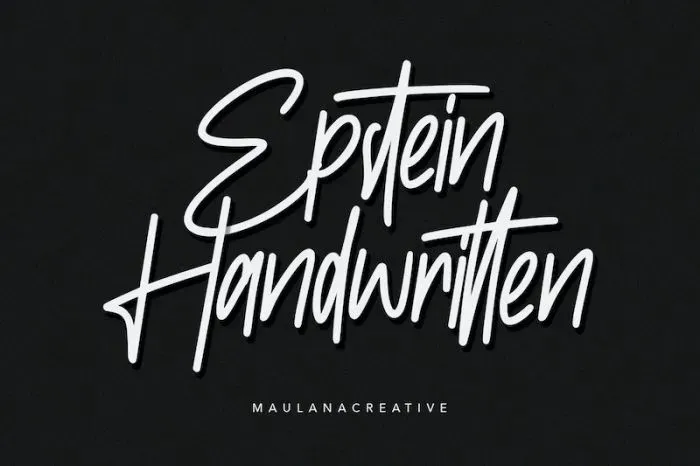
Epstein Handwritten Font – Download Grátis
Epstein Handwritten Font é uma elegante fonte de script monoline criada pela Maulana Creative com uma atmosfera autêntica e descontractual. Esse belo estilo de escrita se destaca para designs que precisam expressar um toque pessoal, como cartões de agradecimento, convites de casamento, cards de festa, logotipos e muito mais. Seja você designer ou não, é uma excelente opção para aqueles buscando dar um visual único e autêntico aos seus projetos, sejam eles pequenos e pessoais ou grandiosos e profissionais. Não hesite em experimentar a Epstein Handwritten Font para adicionar profundidade e personalidade às suas criações de design.